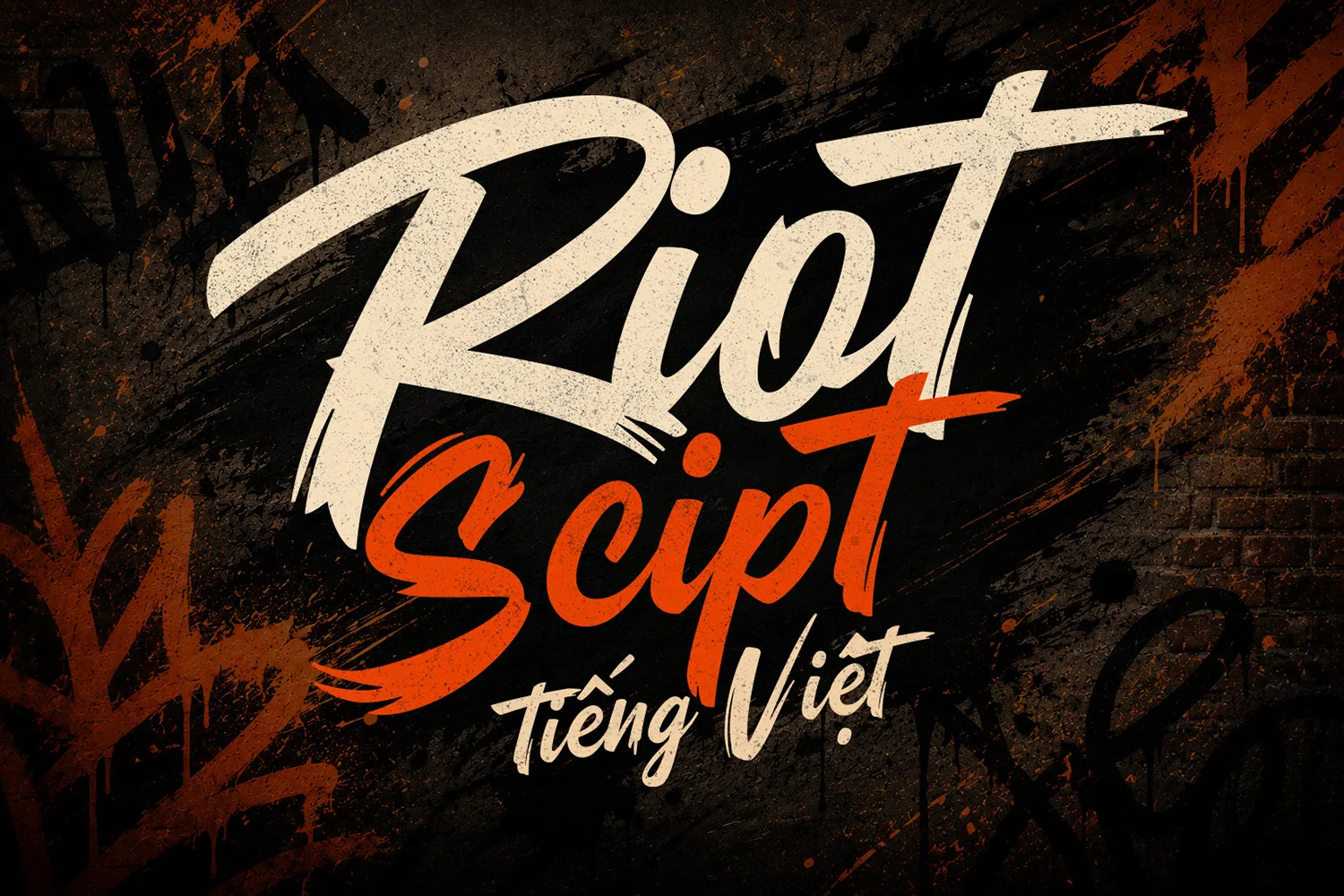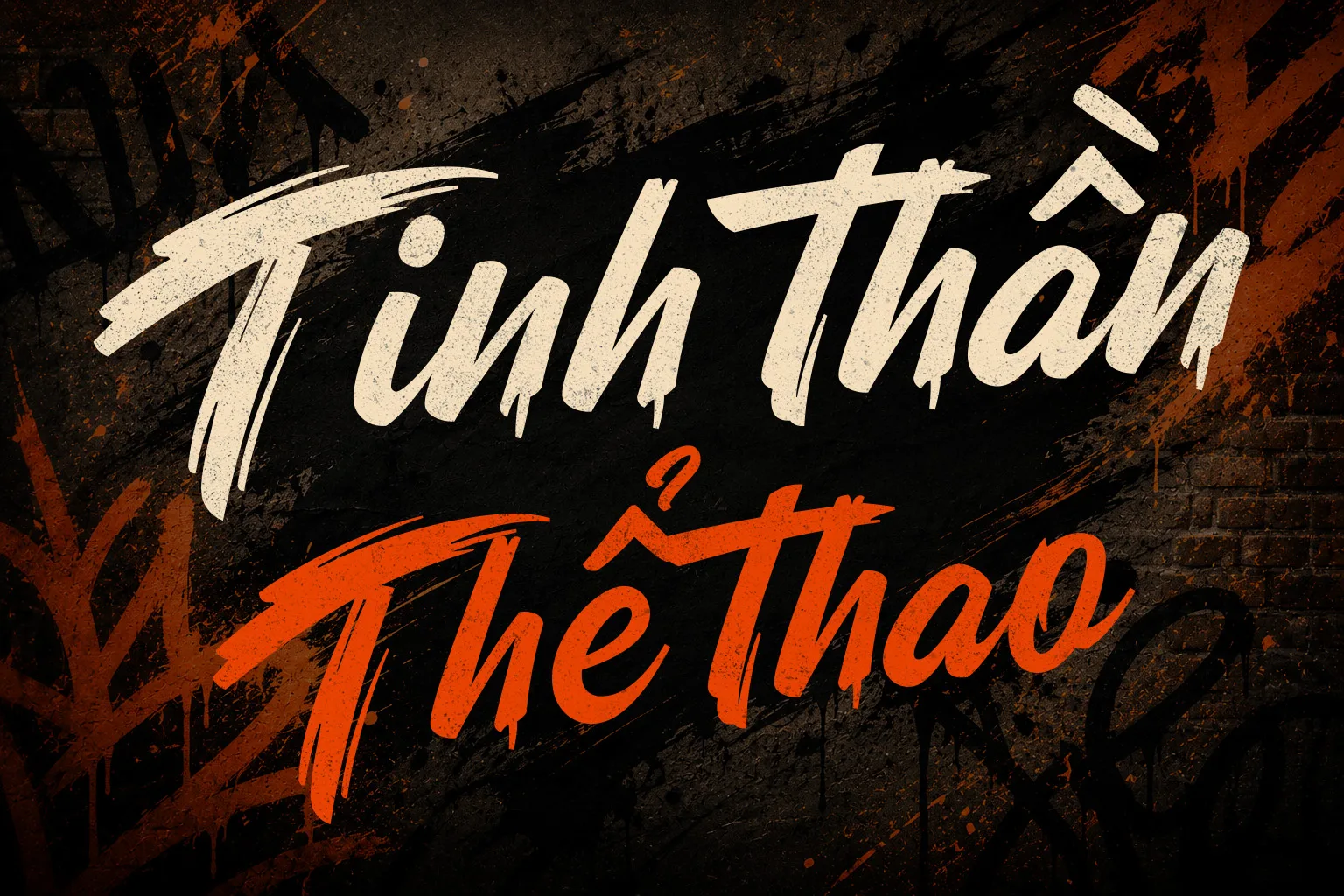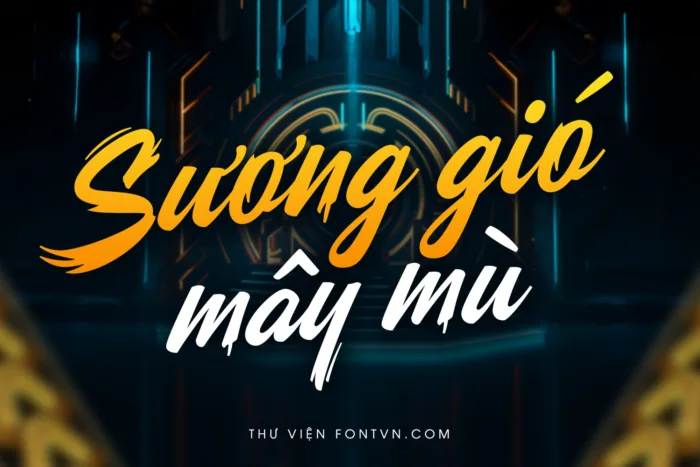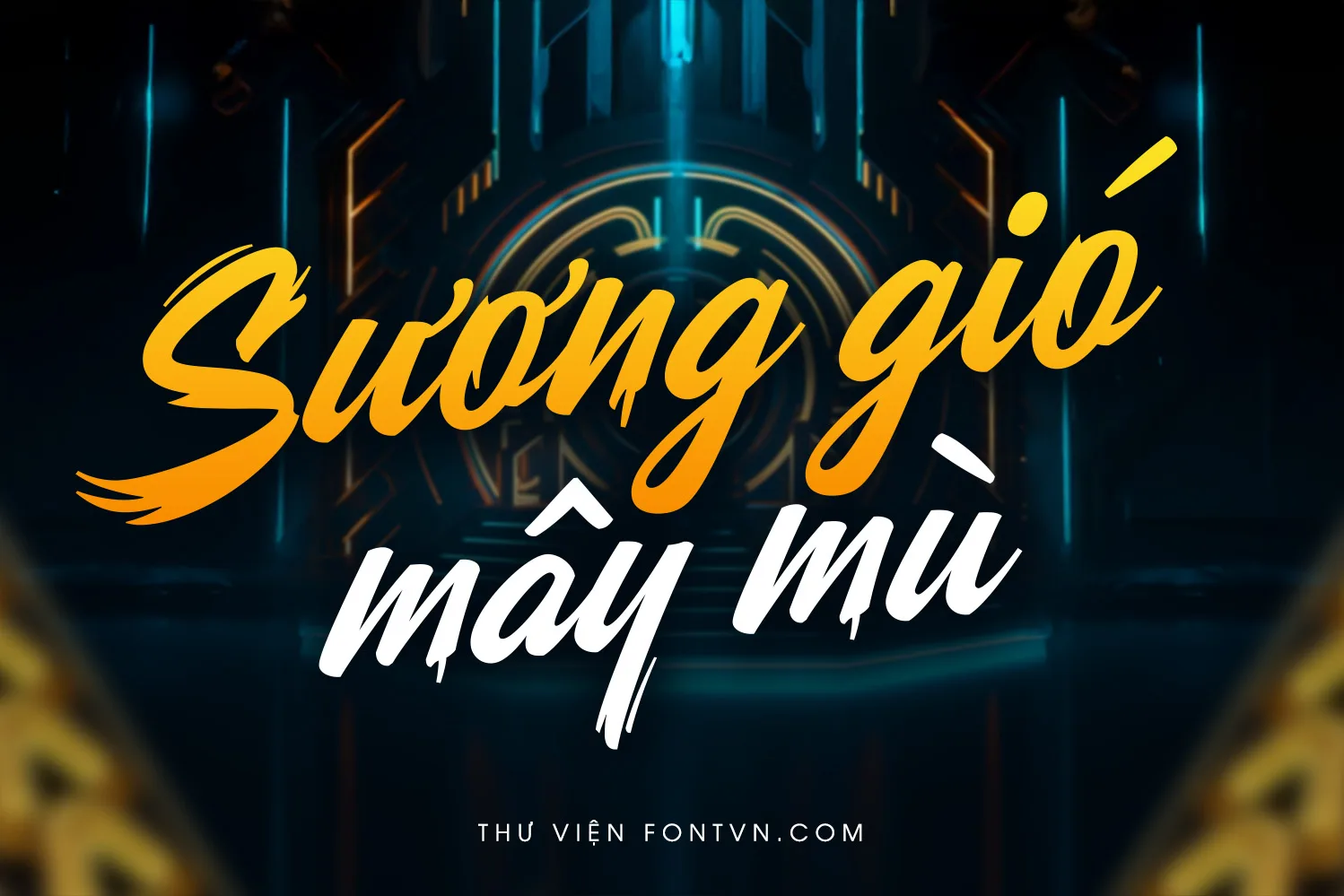
Riot Script tiếng Việt – Font chữ Script năng động và đẹp mắt
DVN Riot Script Tiếng Việt là kiểu chữ brush script mang phong cách vẽ tay đầy ngẫu hứng, lấy cảm hứng từ graffiti, street art và paint brush. Những nét cọ dày, mạnh mẽ cùng các đầu nét sắc nhọn và hiệu ứng quệt sơn tự nhiên tạo nên cảm giác bụi bặm, nổi loạn nhưng vẫn giữ được sự cân bằng và dễ đọc.
Font sở hữu các đường nét chuyển động linh hoạt, độ tương phản cao giữa nét dày và nét mảnh, giúp từng ký tự trở nên nổi bật khi sử dụng ở kích thước lớn. Bộ ký tự tiếng Việt được tối ưu đầy đủ dấu, đảm bảo hiển thị đẹp và hài hòa trong mọi thiết kế.
DVN Riot Script đặc biệt phù hợp với các dự án cần sự mạnh mẽ, năng động và cá tính như thiết kế poster, logo, branding, bao bì, typography, áo thun, banner quảng cáo, thumbnail YouTube, social media, sản phẩm thủ công, đồ uống, cà phê, bia thủ công hay các sự kiện âm nhạc và thể thao.